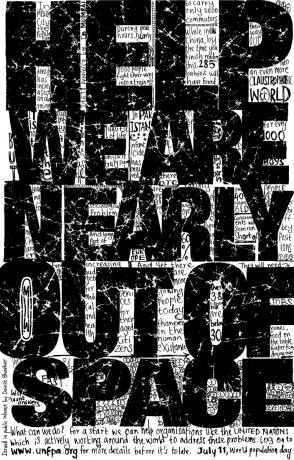
Otra vez la mentada tipografía… y una vez más: excelso. Estupenda idea para el Día Mundial de la Población.
He llegado a la conclusión que una de las pruebas ácidas para un diseñador, es el poder desarrollar un ejercicio expresivo contando únicamente con esta herramienta. Una verdadera experiencia didáctica en composición y creatividad.
Maravilloso uso de la mancha y el aire, audacia en sintaxis con excelentes resultados… y por si fuera poco, a una sola tinta.